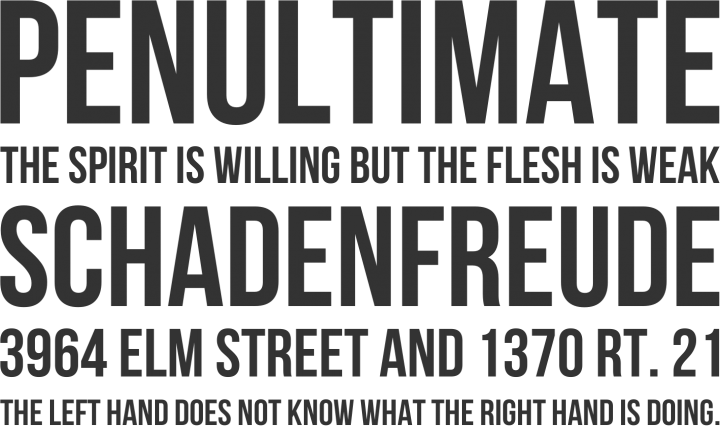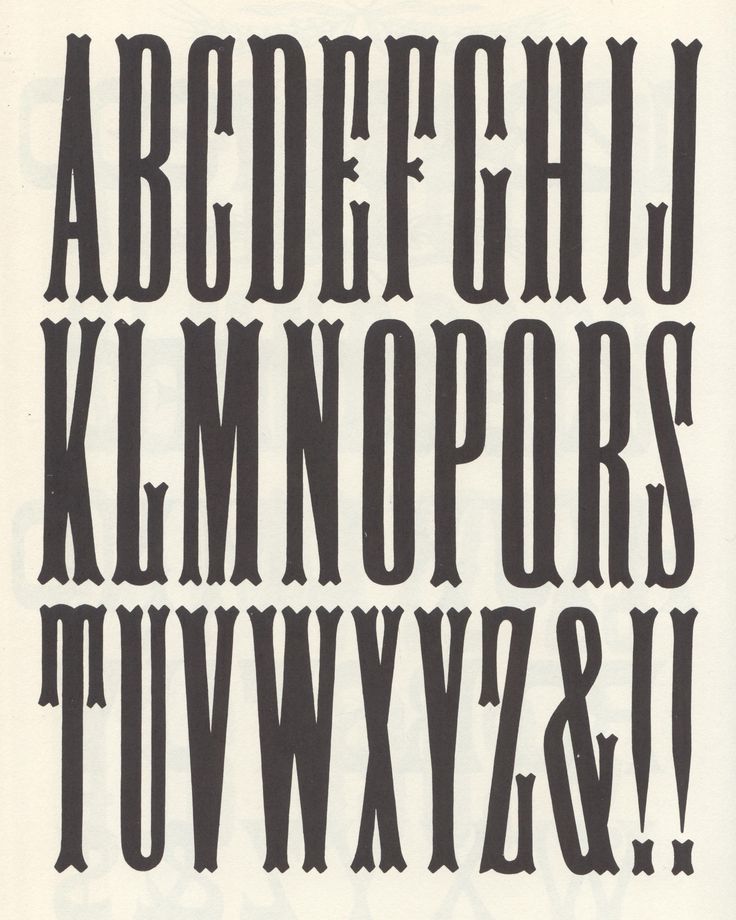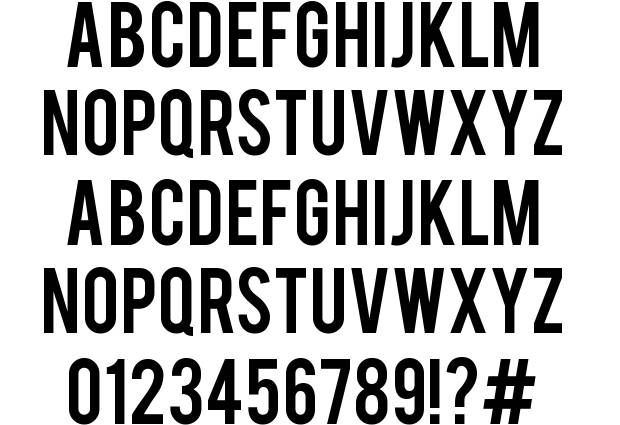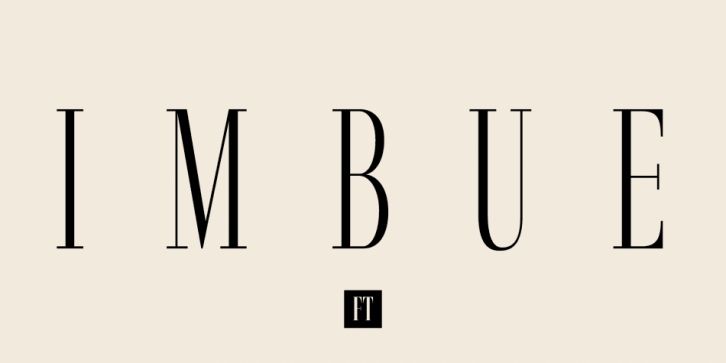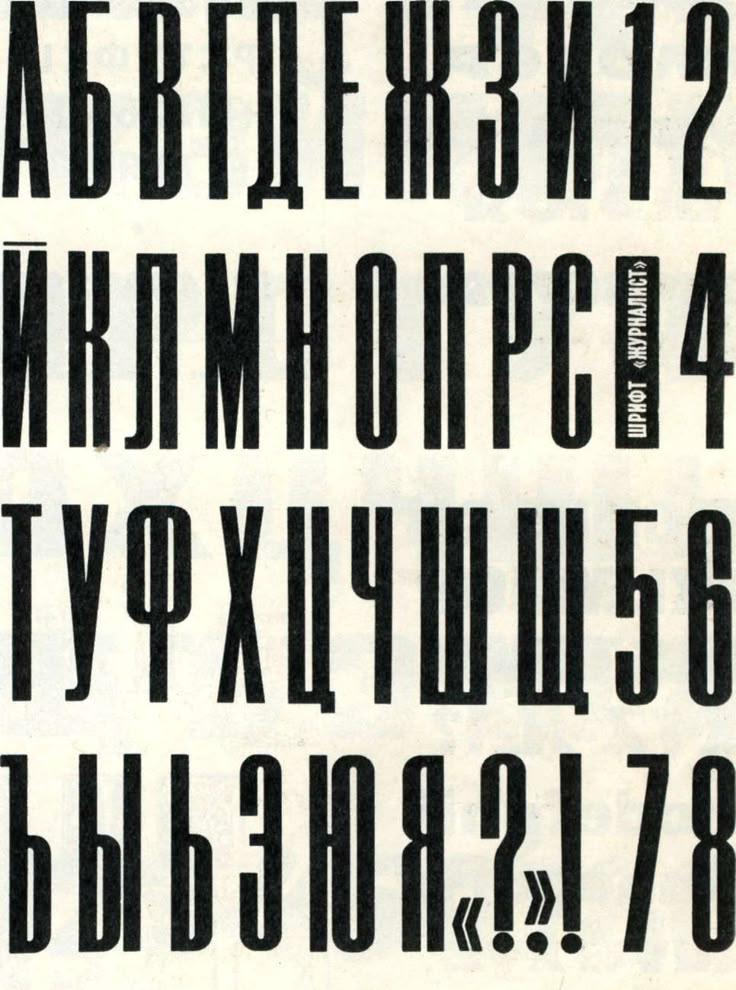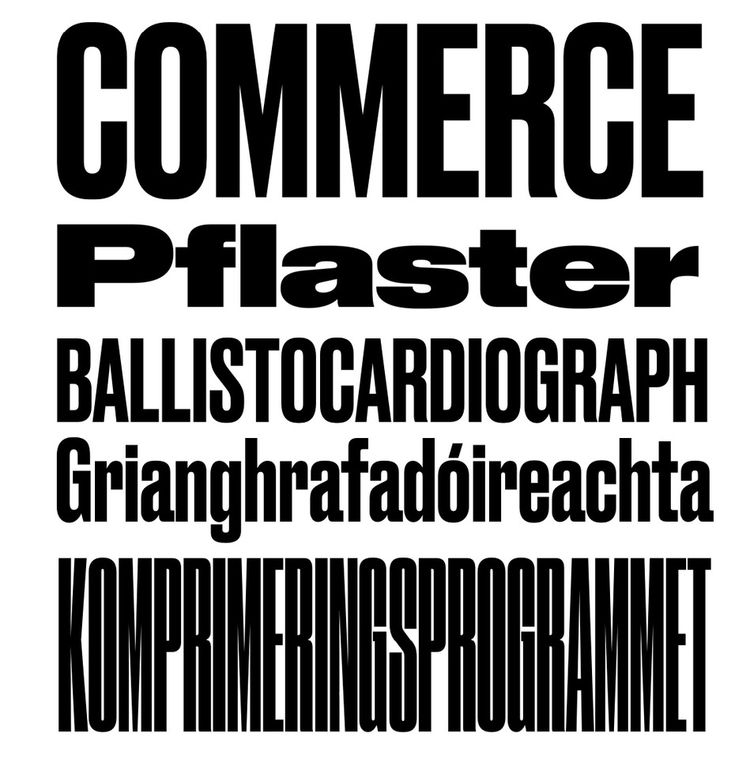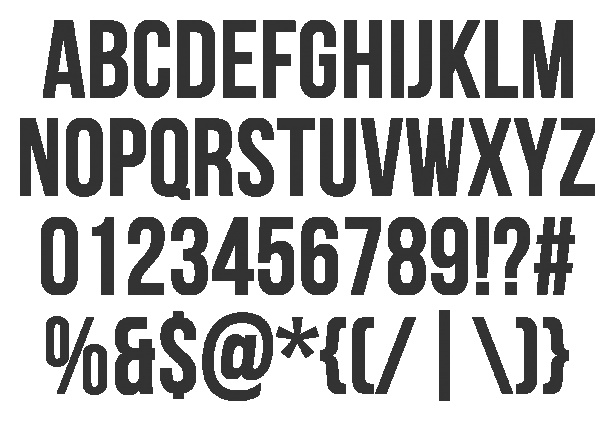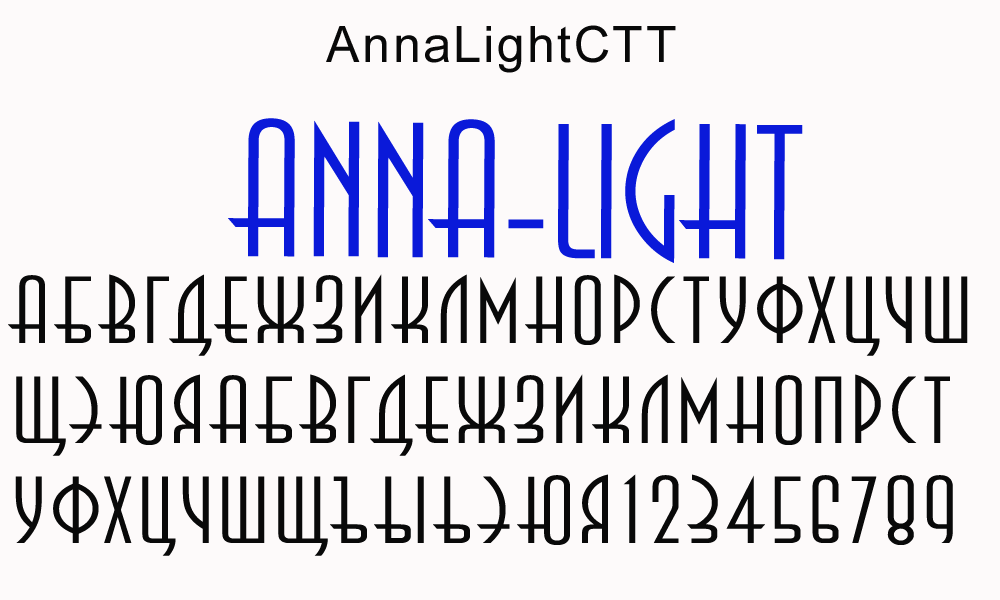
Шрифты высокие: Узкие и высокие шрифты — короткие и сжатые шрифты
Как отдельный элемент фирменного стиля, шрифт не обладает чудесным свойством влиять на уровень продаж. Его «работа» начинается тогда, когда он стает узнаваемым. Таким образом, узнаваемость можно определить ключевым требованием при создании графемы для компании. В этом материале мы расскажем о том, каким образом компания «ARTWELL» генерирует успешные и запоминаемые фирменные шрифты.
Высокие стандарты
Фирменный стиль – это своеобразная «униформа» для бренда, которая должна присутствовать всегда и везде. В студии «ARTWELL» создают не просто «униформу», а настоящие работы Haute Couture. Мы предъявляем к шрифту высокие требования, избегая теоретизации и выстраивая процессы исключительно на реальном практическом опыте.
Как и в любой другой работе, главным критерием оценки является качество результата. Что такое качественный шрифт? Можно определить ключевые параметры:
– простота, понятность, удобочитаемость;
– уникальность, свежесть;
– эстетичность.
Важна целостность всех критериев, отсутствие одного из них рушит идеальную картинку.
Разработка фирменного шрифта ведется одновременно с созданием остальных элементов брендбука. В случае с логотипом и товарным знаком ситуация является более чем определенной: уникальное графическое изображение решает вопрос оригинальности символьной составной корпоративного стиля. Объектная текстовая часть – шрифт – длительный и затратный процесс, требующий особых усилий для того, чтобы была создана абсолютно уникальная, можно даже сказать, эксклюзивная гарнитура шрифтов для Вашего бизнеса. Итог работы: узнаваемость компании по одному только начертанию букв.
Суть в деталях
Список требований к качественному шрифту можно расширять до бесконечности, опустим такие, как «должен влиять, раскрывать, транслировать, вызывать» и т.д. Компания « ARTWELL», имея большой опыт в создании эффективных решений для бизнеса, акцентирует внимание на сугубо практических моментах.
Если говорить о реалиях, то хороший шрифт должен не только быть узнаваемым, но и обладать хорошей, так сказать, «жизнеспособностью» — свойством привлекать внимание всегда и везде. Речь идет о технологичности шрифта.
Это свойство должно присутствовать априори. Говоря о технологичности шрифта, мы подразумеваем его способность давать качественные и точные отпечатки. Визитки, открытки, буклеты, этикетки, бланки – это разные форматы, фон, фактура. В каждом случае шрифт должен смотреться одинаково хорошо. Для этого дизайнеры прорабатывают каждую засечку, тень, исследуют контрастность и определяют оптимальное внутрибуквенное расстояние. Важно, чтобы шрифт не терял своих уникальных черт как и на небольшом флаере, так и на огромной растяжке или биллборде. Только большой опыт, профессионализм, осведомленность в последних технологических достижениях позволяет создавать студии «
Грамотно созданный шрифт может приносить выгоду Вашему бизнесу сразу же. Существуют приемы, которые влияют на убористость шрифта. Это важно для тех компаний, у которых есть необходимость в создании больших объемов печатной продукции. Применение экономичных шрифтов позволяет сократить расходы на бумагу, уменьшить стоимость типографских работ.
Существует множество других нюансов, как, например, подготовка шрифтов для интернациональных рекламных кампаний. «Перевод» (дублирование) фирменного шрифта с латиницу на кириллицу и наоборот занимает много времени и требует глубоких знаний типографики. Будьте уверены, что мельчайшие детали всегда находятся в поле зрения специалистов компании « ARTWELL», фирменный шрифт будет создан с учетом всех нюансов и требований.
При разработке фирменного шрифта задает тон общая концепция, выработанная бизнес-аналитиком компании «ARTWELL» на основе данных, полученных от Вашей компании.
Первичным элементом можно назвать фонему (название бренда), продуцируемую в процессе нейминга. Графема как уникальное написание названия является следующим этапом формирования корпоративной айдентики. Держать руку на пульсе во время всех процессов по созданию Вашего фирменного стиля помогает арт-директор студии «ARTWELL», который ведет проект от начала до конца и контролирует процесс материализации творческих идей в конкретный результат – брендбук компании.
Качественный фирменный шрифт будет одинаково хорошо смотреться в разных масштабах, на неоднородном фоне. Эта задача – в зоне ответственности профессиональных дизайнеров, которые проводят тестирование созданной гарнитуры. В зависимости от поставленных целей, могут быть выведены шрифты для использования по разному назначению: для рекламных кампаний, для технической документации, для официальных документов.
Информация о том, как и где какой шрифт использовать, содержится в брендбуке. Там же собраны правила, описания, рекомендации по применению всех остальных элементов фирменного стиля.
CaledoЭтот сжатый толстый-тонкий шрифт без засечек доступен в двух стилях — легком и полужирном. Смешивайте и сочетайте их в соответствии с вашими потребностями. Высококонтрастный дизайн этого шрифта делает его идеальным для заголовков.
HeathergreenЭтот шрифт похож на упомянутый выше Deutschlander, но он даже выше! Теперь вы можете втиснуть еще больше текста в свои крошечные пространства.
Постер фильма SF Если вы ищете сверхсжатый шрифт для своего проекта постера фильма, этот шрифт подойдет вам. Включает в себя 8 стилей от обычного веса до полужирного.